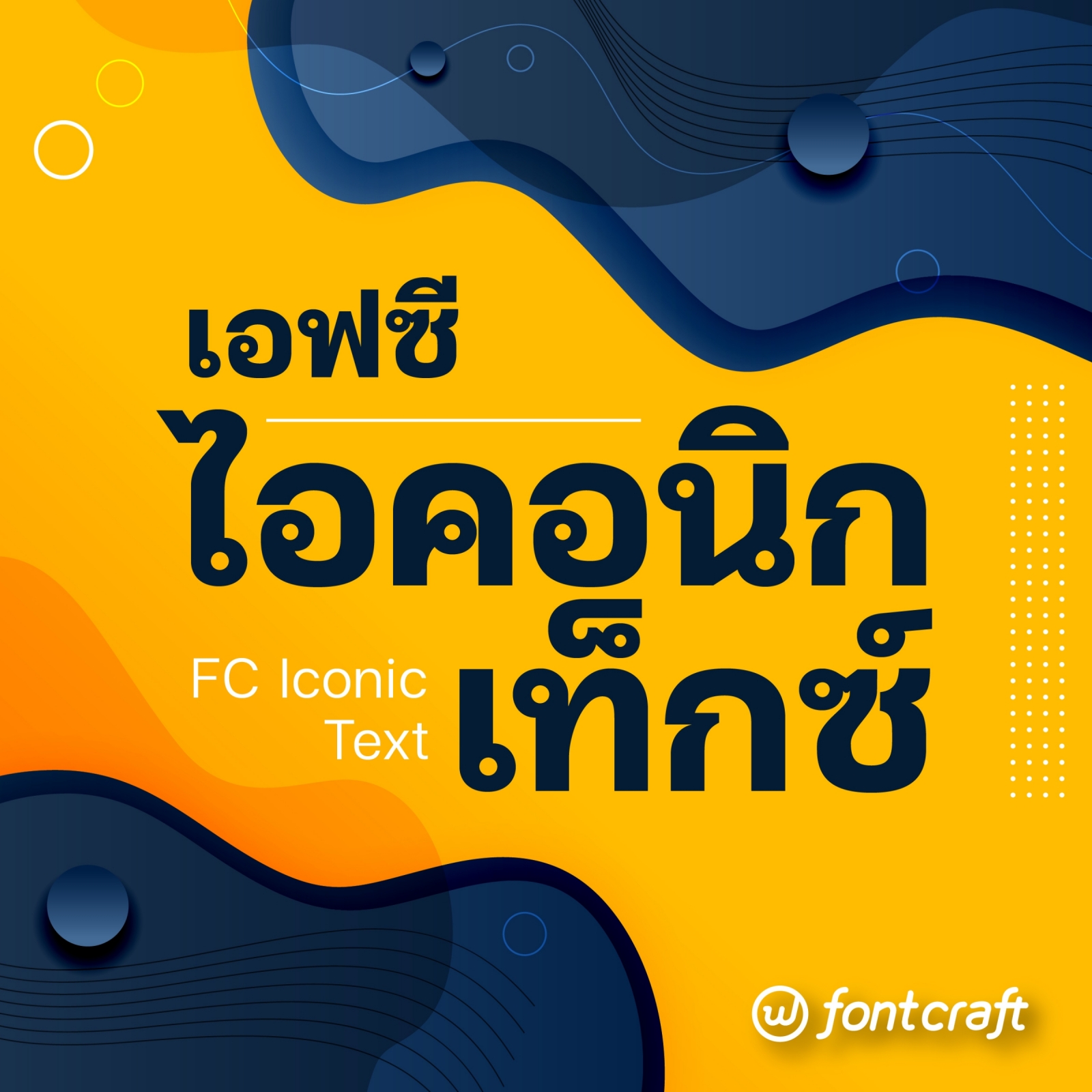
เอฟซี ไอคอนิก เท็กซ์ (FC Iconic Text)
ฟอนต์เอฟซี ไอคอนิก เท็กซ์ (FC Iconic Text)
หลังจากที่ทางเราได้ Feedback จากนักออกแบบส่วนนึงว่า ทำไมไม่ค่อยมีผู้ทำฟอนต์ไทยมีหัวเท่าไหร่ จึงเกิดเป็นโปรเจคพัฒนาฟอนต์เอฟซี ไอคอนิก เท็กซ์ (FC Iconic Text) นั่นเอง
ฟอนต์เอฟซี ไอคอนิก เท็กซ์ (FC Iconic Text)
A Thai Traditional, Twisted นวัตกรรมใหม่ของฟอนต์ไทยมีหัว เพื่อการใช้งานร่วมกับ FC Iconic
จากต้นแบบฟอนต์ไทยไร้หัว เอฟซี ไอคอนิก (FC Iconic) นำมาต่อยอดเป็นฟอนต์ไทยแบบมีหัวดั้งเดิม เพื่อการใช้งานเป็นตัวเนื้อความ ภายใต้ชื่อฟอนต์เอฟซี ไอคอนิก เท็กซ์ (FC Iconic Text)
แม้จะเป็นฟอนต์ไทยแบบมีหัว แต่ยังคงเอกลักษณ์ดั้งเดิมของฟอนต์เอฟซี ไอคอนิกไว้อย่างครบถ้วน มีน้ำหนักให้เลือกถึง 9 น้ำหนัก 18 สไตล์ 36 ไฟล์ฟอนต์ ได้แก่
Thin*, Thin Italic*
ExtraLight*, ExtraLight Italic*
Light*, Light Italic*
Regular, Italic
Medium*, Medium Italic*
SemiBold*, SemiBold Italic*
Bold*, Bold Italic*
ExtraBold*, ExtraBold Italic*
Black*, Black Italic*
หาตัวจับยากจริงๆ คนทำฟ้อนต์หัวกลม
เยี่ยมเลยครับ ชื่นชมการแก้ปัญหาฟอนต์อวบกับหัวกลม  :12:  ..พอวางเทียบกันฟอนต์หัวกลมอ่านง่ายกว่าเยอะมากจริงๆ  มิน่า..โบราณท่านถึงเพิ่มเข้ามา เพราะแต่แรกหัวอักษรไทยก็ไม่ได้กลม ออกจะใกล้กับที่เรียกว่าฟอนต์ modern เสียด้วยซ้ำ